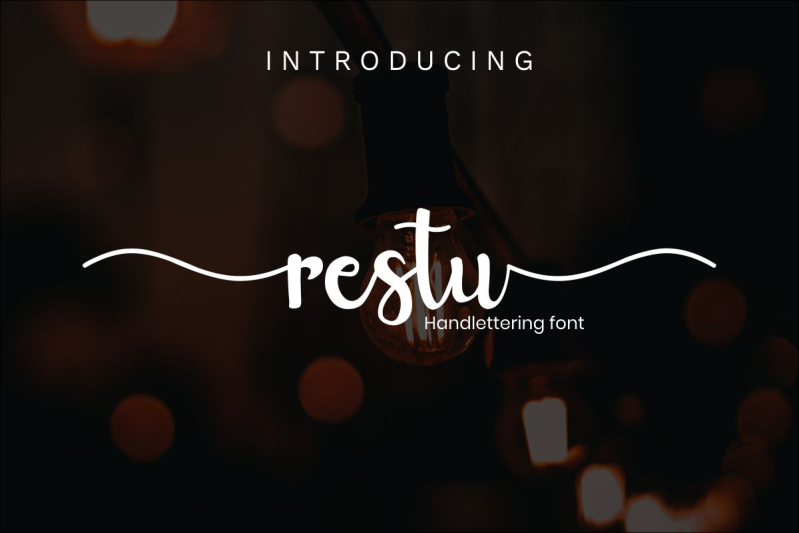
Restu Font – Download Grátis
A fonte Restu é uma elegante escrita à mão criada com delicadeza para designers que buscam uma mistura única entre elegância eterna e autêntica tipografia. Com seu estilo clássico, ainda mantém um tom amigável e descontraído, tornando-o perfeito para criar design único e notável. Para quem está procurando por uma fonte com personalidade que brilha em qualquer projeto de design, Restu é a escolha certa. Ideal tanto para trabalhos profissionais quanto para criações criativas pessoais, essa fonte à mão proporciona um toque diferenciado que torna cada layout um ponto de atenção especial. Se você está procurando por uma novidade na categoria das fontes à mão, Restu é definitivamente algo a ser considerado.